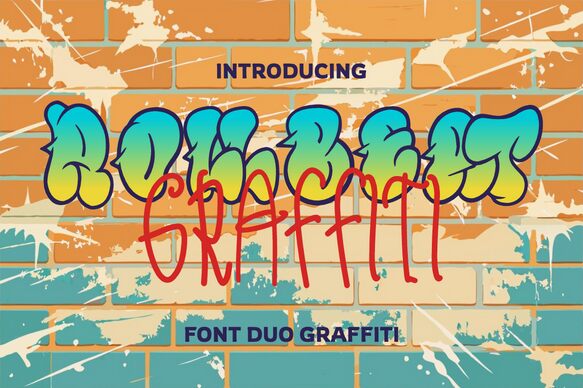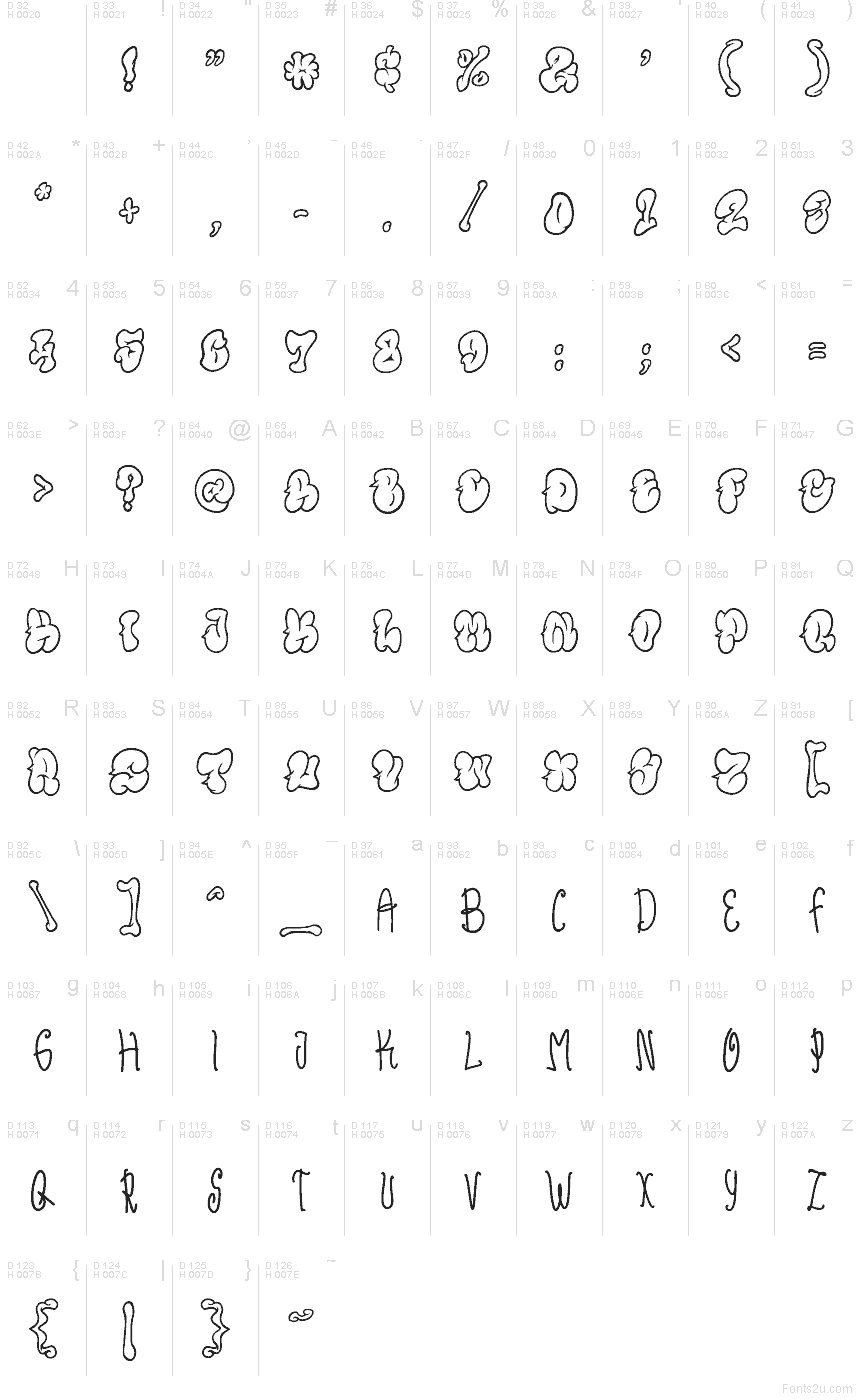
Rollbeat Graffiti
Rollbeat Graffiti Familie zusammengesetzt aus 2 Schriftarten
Rollbeat Graffiti von Shanaf Studio ist eine kostenlose Graffiti-Font in Großbuchstaben, die den lockeren Flow eines Markers mit der Energie klobiger Bubble-Letters vereint. Die Buchstaben bestechen durch geschwollene Kurven, lange, fließende Striche und ein handgezeichnetes Wackeln, das sich anfühlt, als wäre es direkt von einem schnellen Wall-Tag übernommen worden – fernab von jedem polierten Comic-Stil.
Sie passt perfekt zu Streetwear-Branding, Musik-Flyern, Plakat-Überschriften, Skate-Designs und Titelbildern, bei denen eine kostenlose Schrift mit einem authentischen, getaggten Look gefragt ist. Da die Buchstaben auf großen, runden Formen und drahtigen Ausläufern basieren, eignet sie sich auch hervorragend für kurze Cover-Texte, Monogramme und Logo-Entwürfe, bei denen Dynamik wichtiger ist als Perfektion.